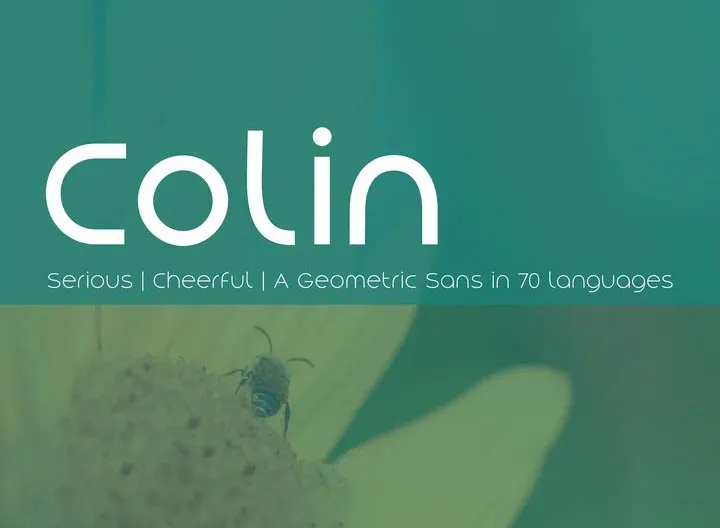
Aqui está uma descrição envolvente e natural para a página de download da font ‘Colin Font’: A font ‘Colin’ é um famoso tipo de sans-serif que surgiu na plataforma 99designs, criado pela Tickbite Type. Esta família de tipos possui uma x-height grande, o que transmite ao mesmo tempo seriedade e alegria. Suportando 70 idiomas, inclusive grego monótono, esta fonte vem em sete pesos diferentes com um número limitado de alternativas de caracteres (ss01), oferecendo mais flexibilidade. O Colin é perfeito tanto para títulos como para seções de exibição e até mesmo parágrafos curtas. Suas figuras fracionadas, old style e tabulares fazem dele uma escolha ótima para design gráfico moderno que busca agradar diversos públicos sem comprometer sua estética. A ‘Colin’ é um tipo de sans-serif moderno e elegante com grande x-height, adequado tanto para uso em textos curtos quanto grandes títulos. Suas figuras fracionadas, old style e tabulares garantem um design fluido que complementa perfeitamente qualquer projeto gráfico. A escolha do Colin para seu próximo projeto de design pode torná-lo único e atraente ao mesmo tempo.